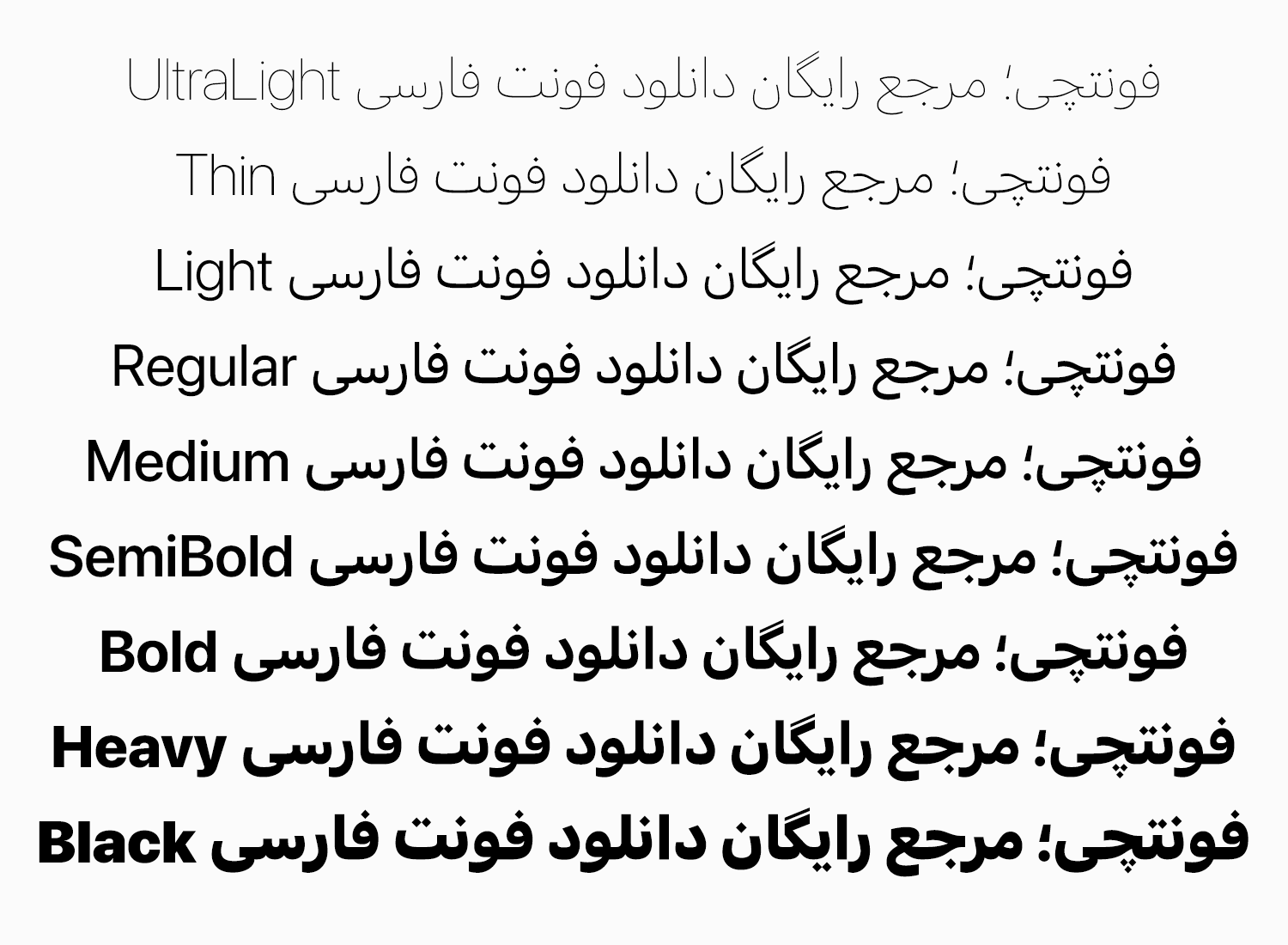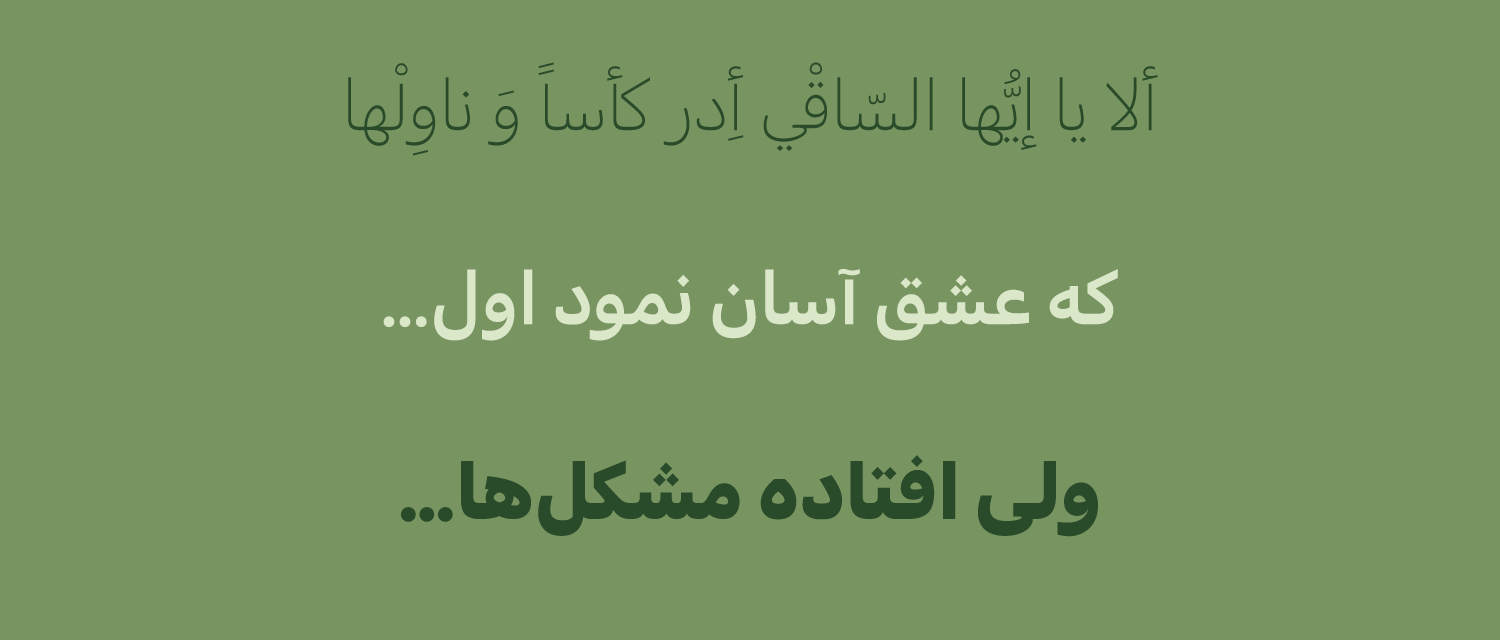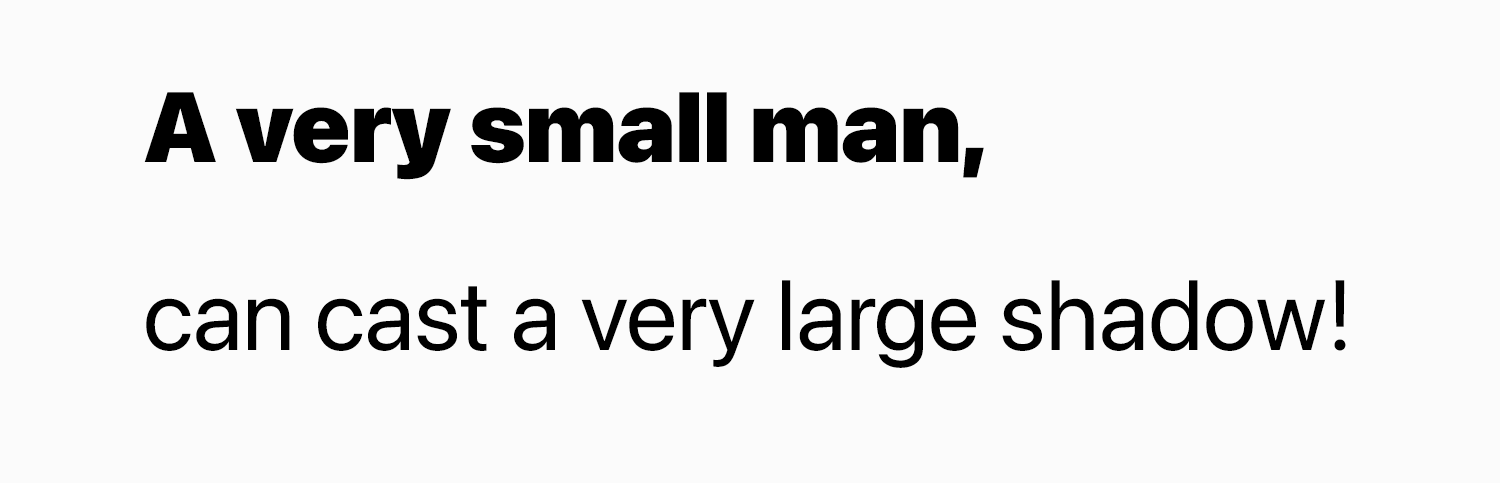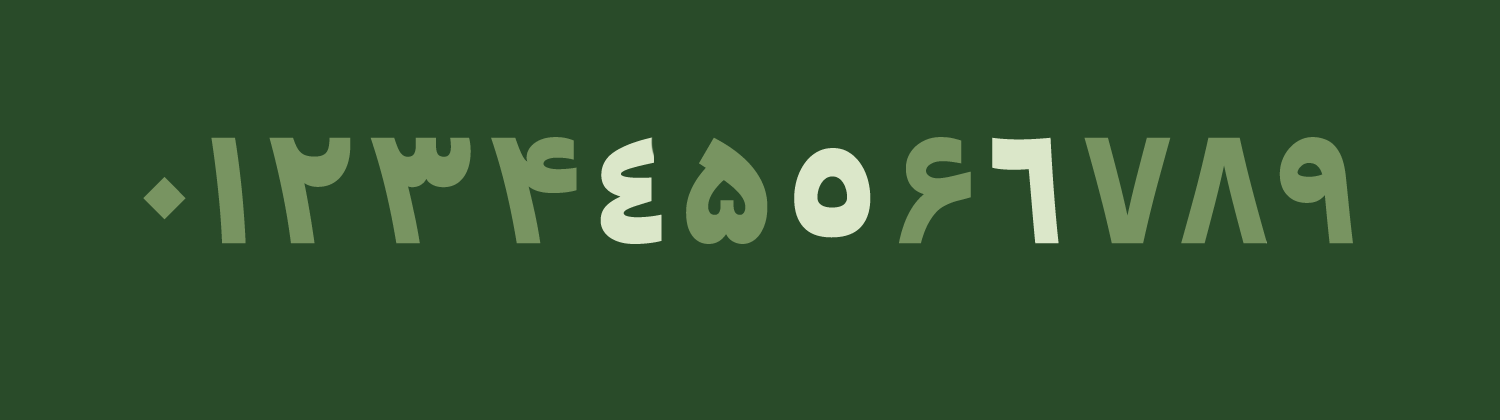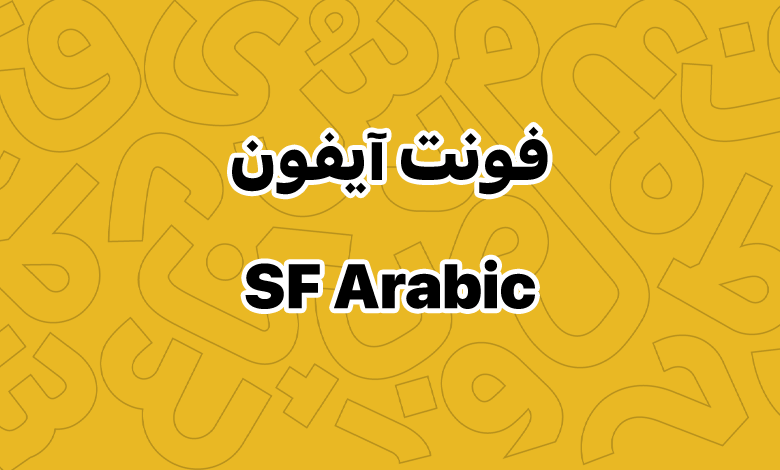
فونت آیفون (SfArabic و SfPro)
فونت اپل (به انگلیسی: Apple Font یا IOS Font) که در محصولات شرکت اپل مورد استفاده قرار میگیرد برای زبانهای فارسی و عربی شامل نسخه SfArabic بوده یا اینکه از فونت سانفرانسیسکو استفاده شده است. بسته به نسخه سیستم عامل این فونت متغیر است. فونت آیفون رایگان در دسترس نیست و نسخههای موجود به شکلی مود شده در دسترس هستند.
فونت فارسی اپل با نام فونت سانفرانسیسکو نیز شناخته میشود. شامل دو نسخه SfArabic و SF PRO است که اگر به دنبال فونت آیفون ترکیبی (فارسی و انگلیسی) هستید، میتوانید از پکی که برایتان آماده کردهایم استفاده کنید.
در ادامه این نوشته از سایت فونتچی به نقد و بررسی دو فونت SFarabic خواهیم پرداخت که در نسخه پایه زبان فارسی و عربی شامل تمامی وزنها به صورت فایل تکی و همچنین وریبل بوده و در نسخه عربی که با نام SF PRO شناخته میشود، یک فایل فونت شامل تمامی وزنها در قالب یک بسته فایل وریبل قرار گرفته است.
ویژگی های فونت آیفون رایگان (SFArabic و SfPro)
فونت آیفون از محبوبترین فونتها برای طراحیهای خلاقانه، در نسخههای SF Arabic و SF PRO ارائه میشود. این فونت که در محصولات اپل استفاده شده، از زبانهای فارسی، عربی و لاتین پشتیبانی میکند. کاربران میتوانند با دانلود این فونت ترکیبی، پروژههای طراحی یا تولید محتوا خود را با جلوهای حرفهای ایجاد کنند.
- پشتیبانی از زبانهای متنوع
- نسخه SF Arabic برای زبانهای فارسی، عربی، کردی، اردو و ترکی مناسب است.
- نسخه SF PRO برای زبانهای لاتین طراحی شده و از حروف خاص زبانهایی مثل فرانسه و ترکی استانبولی نیز پشتیبانی میکند.
- طراحی و وزنهای فونت آیفون
- وزنهای فونت آیفون شامل ۹ وزن نازک تا سنگین است.
- فونت وریبل آیفون (Variable) امکان دسترسی به تمامی وزنها را فقط با نصب یک فایل فراهم میکند.
- پشتیبانی از اعداد فارسی و عربی
- اعداد بهصورت استاندارد بسته به زبان صفحهکلید (فارسی یا عربی) تایپ و نمایش داده میشوند. با دانلود فوت آیفون برای فتوشاپ میتوانید از طریق پنل گلیف به دلخواه از اعداد ترکیبی نیز استفاده کنید.
کاربرد فونت آیفون در طراحی
- شبکههای اجتماعی: طراحی استوری و پست برای اینستاگرام یا تامنیل برای یوتوب با این فونت، جلوهای حرفهای و جذاب ایجاد میکند.
- سایتها: استفاده از وزنهای سنگین برای عناوین و وزنهای معمولی برای متنها، تجربه کاربری بهتری فراهم میکند.
- طراحی گرافیکی: فونت آیفون در قالب وریبل، انعطاف بالایی برای پروژههای گرافیکی ارائه میدهد. خصوصا اینکه ظاهری شیک و با اصالت را با توجه به تفکری که محصولات اپل در ذهن مردم ایجاد کرده به برند و محصول شما خواهد داد.
بسیاری کاربران اینستاگرام، یوتوب یا تلگرام، ترجیح میدهند از فونت اپل برای پستهای خود استفاده کنند. خصوصا در صفحات فروشگاهی که دلیل بیشتر آنها به کلاس کاری مربوط میشود.
با دانلود فونت فارسی آیفون برای اینشات میتوانید پستها و استوریهای خود را با وزنهای مختلف این قلم طراحی کنید. برای ویدئوهای کانال یوتوب هم میتوانید تامنیلهای خود را با این قلم طراحی کنید یا حتی در برنامه کپ کات روی ویدئو متنهای مختلف درج کنید. در مجموع این قلم نرخ کلیک را افزایش داده و به رشد صفحه شما کمک خواهد کرد.
از فونت آیفون ضخیم که در وزنهای Black و Heavy ارائه شده میتوانید در عناوین، تیترها، نقلقول و باکسهای رنگی استفاده کنید تا از نظر وزنی موجب جلب توجه بیشتر کاربران خواهد شد. از سوی دیگر از نسخه معمولی و بولد هم میتوانید برای متن استفاده کنید.